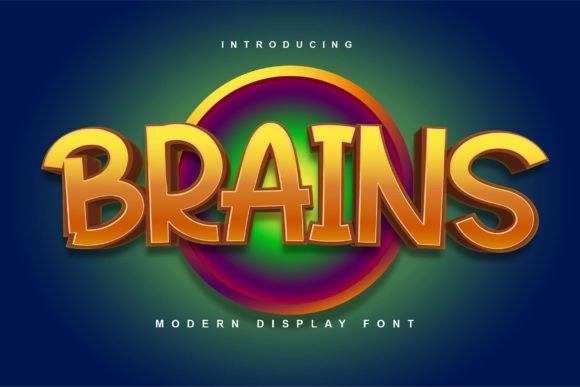
Creativefabrica Brains Font
[Creativefabrica] Brains Font
Brains - это красивый и стильный шрифт.
Благодаря веселым и уютным символам, этот шрифт подходит для широкого спектра дизайнов, таких как детские игры, заголовки, названия брендов, журналы и другие!